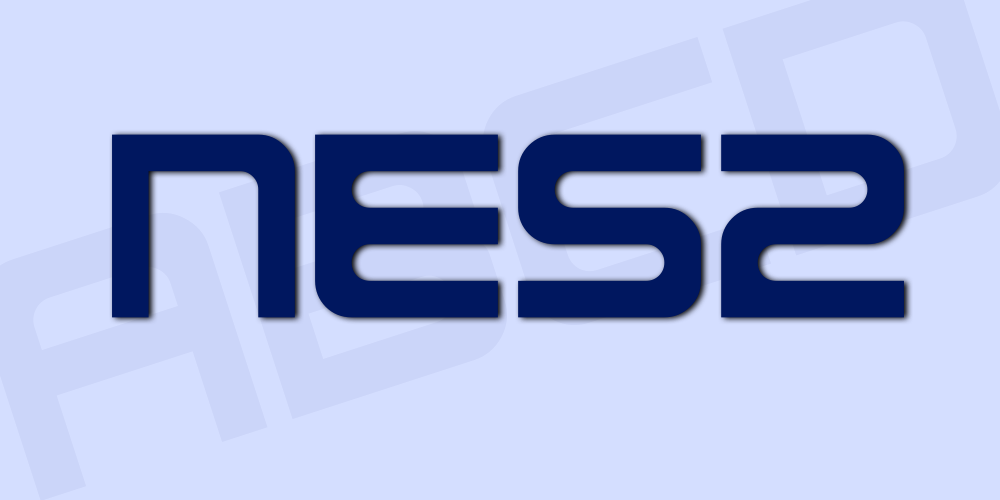
A NES2 font é uma tipografia sans-serif que acaba de ganhar novos ares com a adição de alguns sinais morfográficos e símbolos. Ideal para aqueles buscando um estilo moderno que se destaca, esta nova versão do Hamilton cria um espaço onde você pode expressar ideias de uma maneira única e criativa. Com um design leve e contemporâneo, NES2 oferece flexibilidade em qualquer tipo de projeto gráfico — seja no layout digital ou impressa. Seja para criar headlines atraentes ou apresentações de PowerPoint impressionantes, a NES2 font será sua melhor aliada.